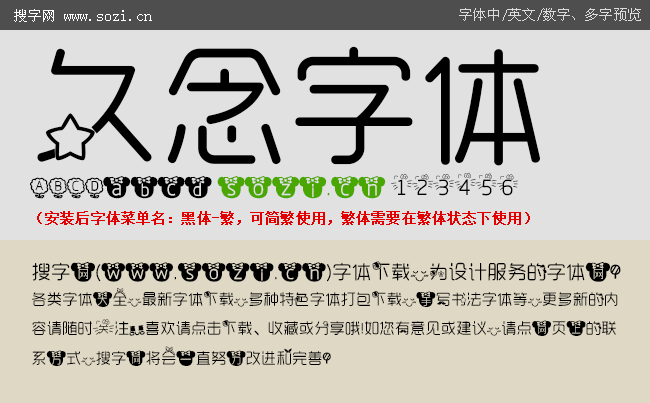
久念字體
搜字網(wǎng)給大家提供一款久念字體手機中文字體下載。這款手機字體是將悅圓體字體為原形,字體間嵌入可愛的卡通圖案。造字工房悅圓常規(guī)字體為圓體字形,結(jié)構(gòu)秉承悅黑系列,筆畫風(fēng)格簡潔,柔美優(yōu)雅。加入卡通圖案后趣味性實足,又保持了文字的識別度,特別適合喜歡手機字體個性一些的朋友在手機上安裝使用。